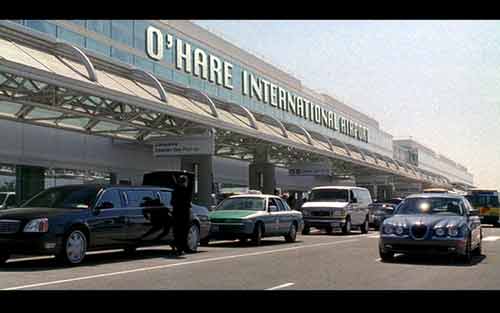
Nie eine Schrift wegen ihres Namens waehlen»Ich glaub’, ich bin im falschen Film« dachte sich der
kanadische Schriftexperte, Designer und Hochschullehrer Matt Soar, als er auf
der heimischen Videoanlage die DVD Meet The
Fockers einlegte (dt. Titel: Meine Frau, Ihre Schwiegereltern und ich). Eine
Szene zu Filmbeginn zeigt angeblich die Halle des Chicagoer Flughafen
O’Hare International Airport, ist jedoch leicht als Kulisse zu
entlarven, weil sie mit der alten Mac-Systemschrift »Chicago«
Nun weiß man ja, dass Drucksachen und Beschriftungen in Filmen meist
frei interpretiert – wenn nicht sogar frei erfunden – sind. Niemand
wird dem Regisseur Jay Roach vorwerfen, dass er die Szene, in der Ben Stiller
mit seiner zukünftigen Braut zu deren Eltern fliegen, nicht am
Original-Schauplatz drehen konnte, dem Flughafen O’Hare in
Chicago:
![]() Flughafenszene aus Meet The Fockers (Quelle: Matt Soar) Dem Filmausstatter muss sich jedoch vorwerfen lassen, das Ersatzgebäude mit einer ziemlich unglaubwürdigen Schrifttype verziert haben zu lassen. Man sieht dem ungeschliffenen Schriftzug nicht nur seine Herstellungsweise an – die Postproduction –, die gewählte Schrift entlarvt die Arbeit darüber hinaus als unüberlegten Schnellschuss. Der Font heißt zwar Chicago (1983 von Susan Kare für die Beschriftung der Macintosh-Menüs entworfen), hat aber sonst keinen Bezug zur Metropole am Michigan-See. Matt Soar schreibt: »It’s design has absolutely nothing to do with the city of the same name. In fact, according to Kare herself, the set of fonts she designed for Apple ›were named after Philadelphia suburbs«, until management decided otherwise.« Die Moral von der Geschicht’: Wähle nie eine Schrift wegen ihres Namens aus! Herausgegeben: Di - Januar 10, 2006 at 12:06 nachm. | |